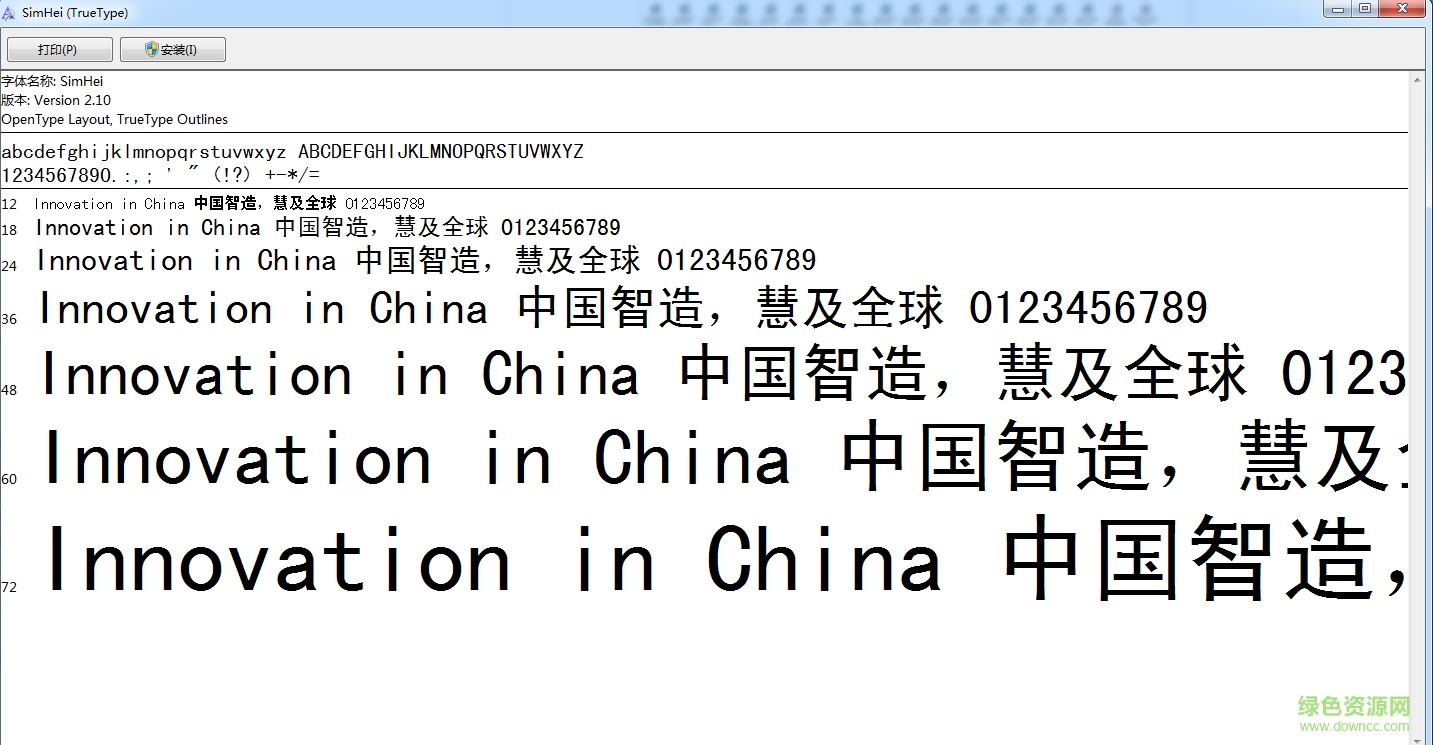
開(kāi)票系統(tǒng)黑體字體是一款常常用于電腦開(kāi)票軟件的黑體字體,該字體線條粗細(xì)相當(dāng),結(jié)構(gòu)端正,印刷效果清晰明快,整體莊重大方,有需要者歡迎在綠色資源網(wǎng)下載!
開(kāi)票黑體字體筆畫(huà)干凈簡(jiǎn)練毫無(wú)裝飾,線條流暢自然,字形端正大方,適合用于各種正式書(shū)面文件或排版方面!
黑體與白體相反,沒(méi)有襯線裝飾,筆劃粗壯有力,撇捺等筆畫(huà)不尖,使人易於閱讀。黑體是在現(xiàn)代印刷術(shù)傳入東方後依據(jù)西文無(wú)襯線體所創(chuàng)造的。所以黑體這個(gè)詞的范疇和無(wú)襯線字體是類(lèi)似的。而宋體就可以被稱(chēng)作襯線字體。